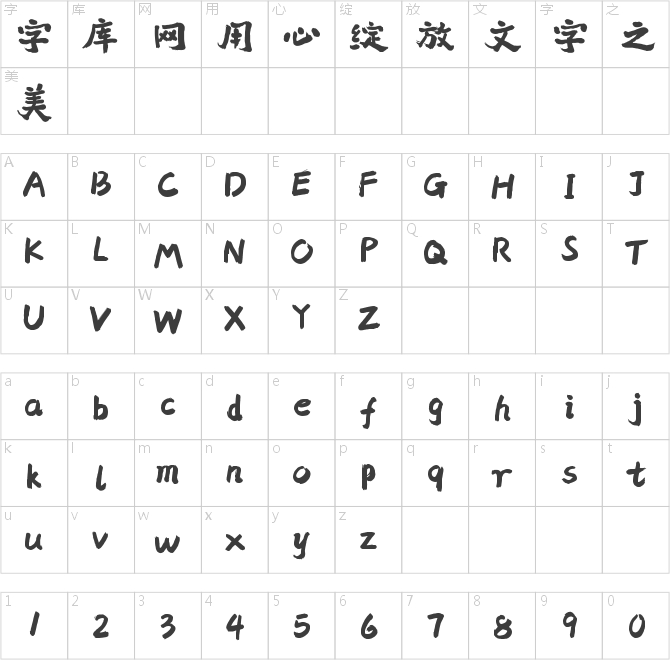
字魂225号-暮云手书
字魂225号-暮云手书是一款书法字体。字体巧妙将传统书法和现代字体设计相融合,用笔洒脱豪放,笔触中增加了飞白处理,适用于宣传设计,商业类的品牌广告和产品包装设计。
字魂225号-暮云手书字体zihun225hao-muyunshoushu字库是一款让人赏心悦目、百看不厌的中文字体,适合各类广告和产品包装设计应用,字体大小15.43MB,格式为ttf字体,上传用户是多喝烫水,作者/版权方为字魂